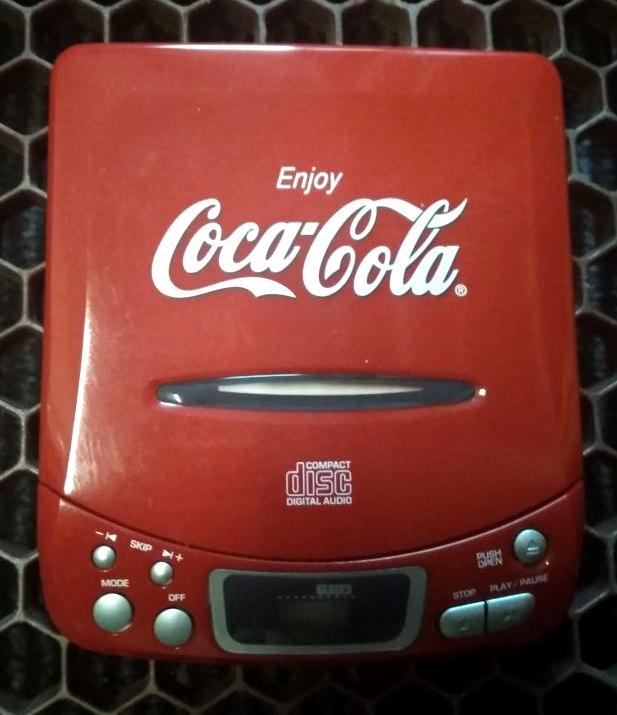
Schriftart "Spencer"/Coca-Cola gesucht
ich suche nach der ORIGINALEN Schriftart von "Coca-Cola". Ein Blogartikel schreibt, dass der Font "Spencer" heißt, ohne weiter Infos dazu. Es gibt die Schriftart als "Loki-Cola", aber das ist nur eine frei erstellte Kopie. Ein Font "Spencer" habe ich im Internet nicht gefunden. Ist es möglich, dass der überhaupt nicht digitalisiert vorliegt? Wie kommt man dann an den ran?
Erstmal zum Thema. Eine "Spencer" Schriftart gibt es eventuell wohl doch nicht direkt. Es gibt "Spencerian Script" als Schriftstyle und da unzählige Schriftarten, von denen sich manche nur minimal unterscheiden.
Die Buchstaben von "Coca-Cola" sind in der Schriftart "Loki-Cola" vorhanden. Somit ist das wohl ein "Spencerian Script" Schriftstyle und somit eine "Spencer". Aber die "Loki-Cola" ist von ~1990, der Schriftzug "Coca-Cola" älter. Also besteht die Möglichkeit, dass es nie eine (komplette) "Spencer" mit den Buchstaben von "Coca-Cola" vor 1990 gab.